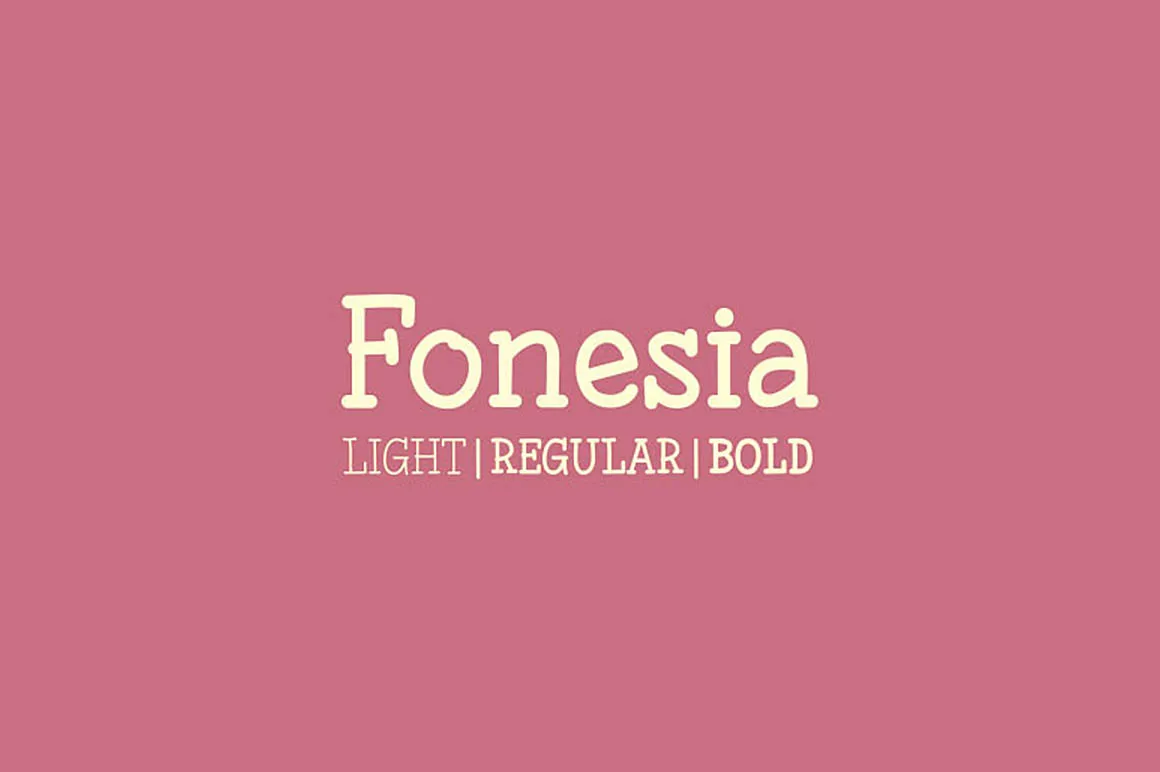
A Fonesia Font é uma elegante fóntes serif criada pelo designer Hamilton. Inspirada na técnica artesanal do desenho a mão, essa fonte traz um toque criativo que será perfeito para seus trabalhos de arte inovadores e sofisticados. Seja você um designer gráfico ou desenvolvedor de sites, a Fonesia oferece uma escolha irresistível para dar um toque único em suas criações. Esta fóntes serif é ideal tanto para aplicações digitais quanto impressas, tornando-a uma opção versátil e divertida. Baixe e deixe-se encantar por esta fonte customizada de qualidade que certamente enriquecerá seus projetos.